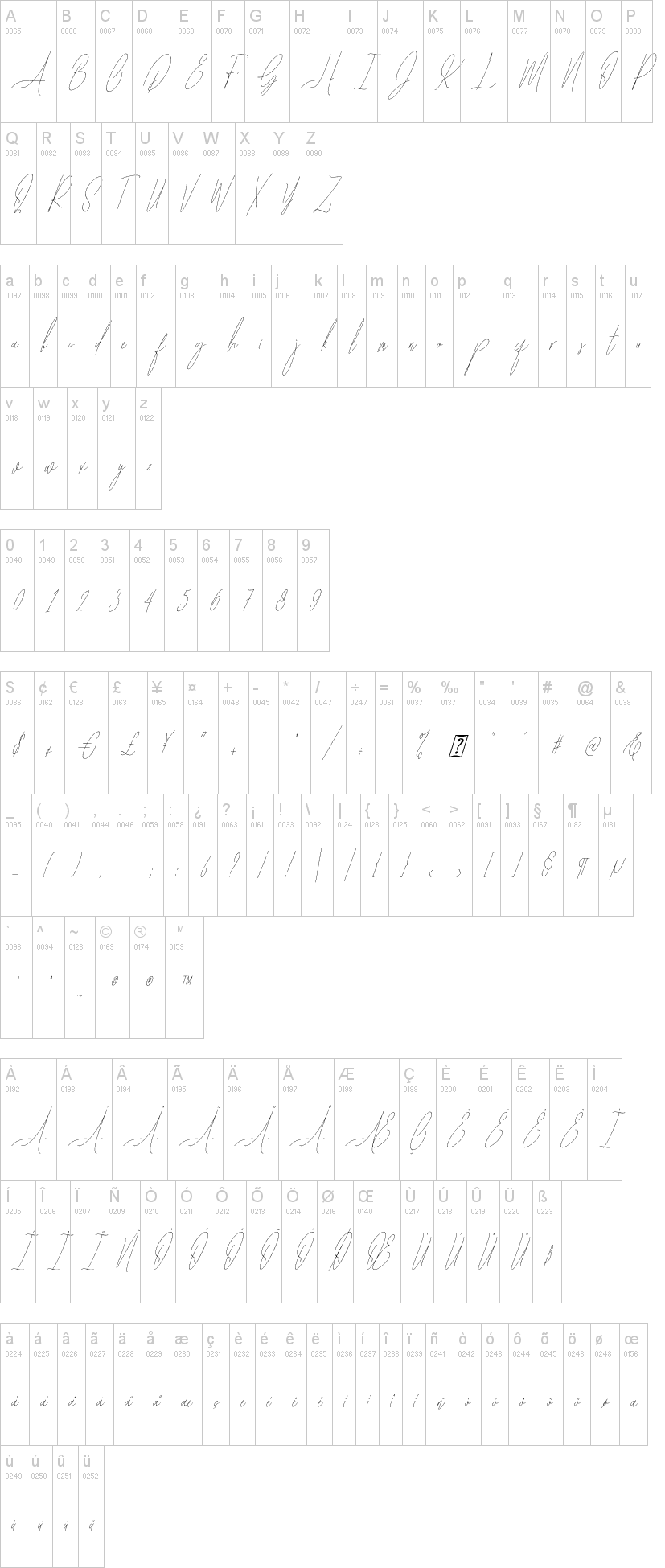
Diamante Signature
? Diamante Signature 字体是一种精致的手写字体,它具有优雅的线条和流动的字形,表达出柔和的精神。它的字型具有温暖的气息,可以让文字更加活泼和有趣。Diamante Signature字体可以用于许多不同的文字应用,包括标题、标签、标语、标志、海报、商业印刷品等等。
Diamante Signature是一款非常不错的手写艺术字体,具有很好的视觉感,适合于文化类的宣传设计、商业类品牌的广告和产品包装设计以及个性化文字排版等较多场景。
Diamante Signature字符映射图